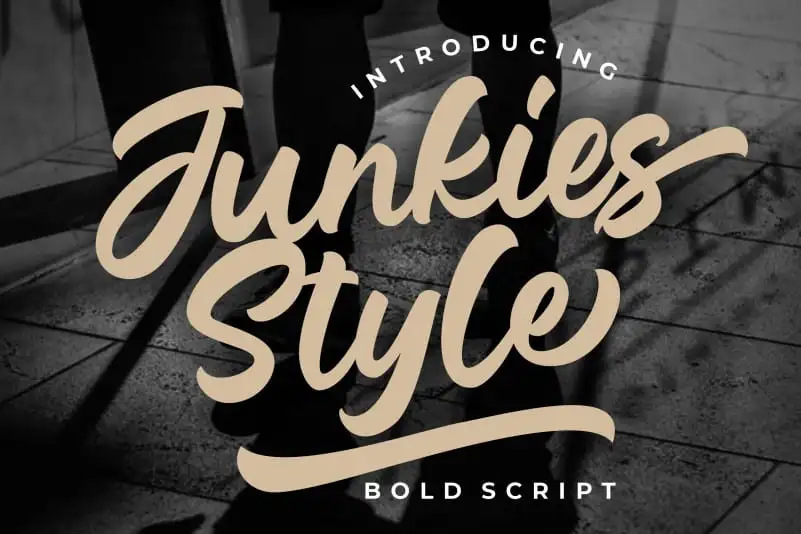
Junkies Style Brush Font – Fonte Grátis
Junkies Style Brush Font
Junkies Style Brush Font é uma elegante escolha para designers que desejam adicionar um toque vibrante e autêntico a seus projetos digitais. Desenvolvida pela equipe criativa do Creatype Studio, esta fonte retrata a essência do street style na medida certa de modernidade e frescor. Conhecida por sua aparência agitada e escrita manuscrita em tração, ela combina com qualquer tipo de projeto que busque um toque único e vibrante. Ideal para aplicação em logotipos, materiais gráficos e identidades digitais, este estilo atraente encaixa-se perfeitamente nos estilos script e brush. Com uma forte presença visual e características fluidas, essa fonte é o ideal para quem busca dar um toque moderno à sua marca ou projeto pessoal. Ideal tanto para aqueles que buscam uma referência vintage quanto para os que desejam criar algo completamente inovador, Junkies Style Brush Font oferece uma combinação perfeita de rusticidade e sofisticação.